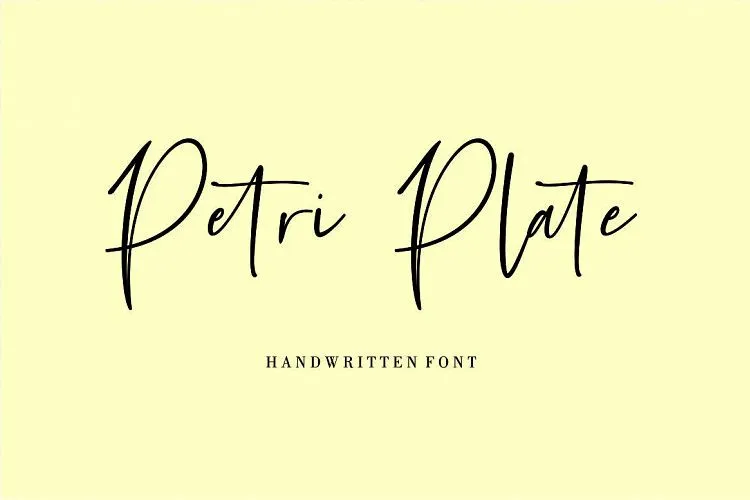
Petri Plate Handwritten Font – Download Grátis
A fonte Petri Plate é uma elegante novidade no gênero de fuentes script. Ela foi criada pelo designer zziplex especialmente para aqueles que buscam um toque de elegância e modernidade em seus projetos digitais. Desenvolvida com precisão, Petri Plate se destaca como uma fonte escrita a mão contemporânea e fashionista. Ideal para aplicações variadas como logotipos, marcações, convites, subtítulos, designs de casamento, posts no Facebook ou Instagram, anúncios, embalagens de produtos, criação de produtos, rótulos, fotografia, marcas únicas, eventos especiais, revistas e design web. Petri Plate é uma fonte de escrita a mão perfeita para qualquer projeto em que deseje adicionar um toque único e moderno ao seu trabalho.